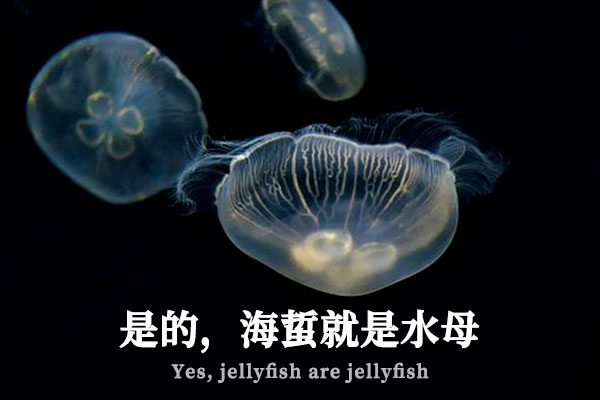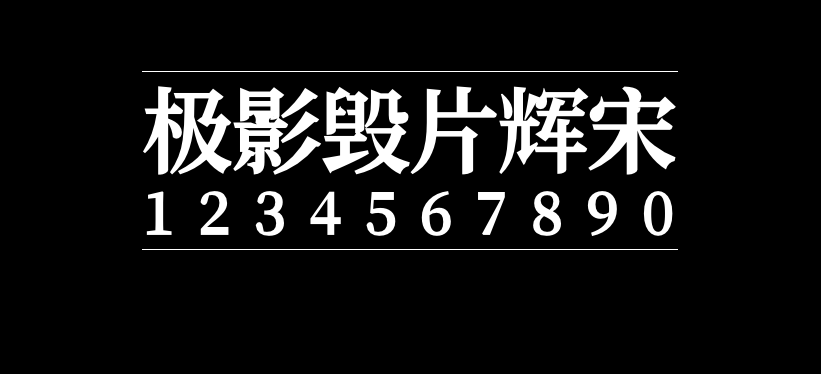
极影毁片辉宋
极影毁片辉宋(KTXP-Kaguya-Serif-Bold)是中国大陆的九阳飞羽将Noto Serif Bold(即思源宋体Bold)进行修改而成的字体。本字体是在原字形的基础上纵向加粗,使得字体里横向的笔画变粗的修改字体。
本字体支持简体中文、繁体中文、日语的字符显示。在字幕制作中,偶尔会用到类似标题宋的字体。不过在字幕的显示上,与某国内著名字体设计品牌的中宋体相比,思源宋体字体家族的横向太细,以至于很难看清(自由君也深感如此)。所以作者将思源宋体的横通过程序加粗,使得它能够在字幕显示上更好地被分辨。